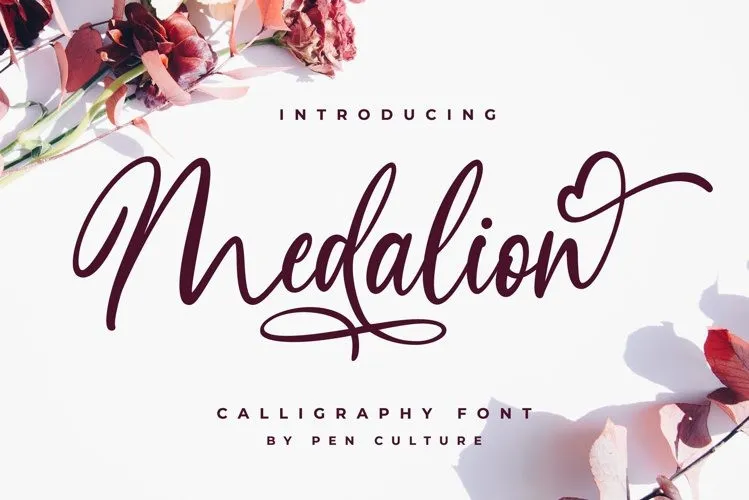
A Medalion Font é uma tipografia script chamada para quem busca um estilo elegante e sofisticado. Esta nova adição ao universo das fonts scripts foi criada pelo site 99designs, apresentando características distintas que complementam o estilo clássico da calligrafia cromada. Com uma mistura única de mão-dupla com a chamada cromada, essa font é perfeita para quem quer dar um toque de elegância em projetos de marca, cartões de casamento e convites. Composta por alternativas interessantes de caracteres, essa font se destaca pela sua versatilidade, sendo uma ótima escolha para designers que buscam personalização nos seus trabalhos. Seja você um designer profissional ou iniciante, a Medalion Font oferece uma opção incrível para expressar o seu estilo em projetos de design gráfico. Seja em cartões de casamento delicadamente escritos, identidades de marca elegantes ou qualquer projeto que exija um toque sofisticado e personalizado, essa font é perfeita para você.